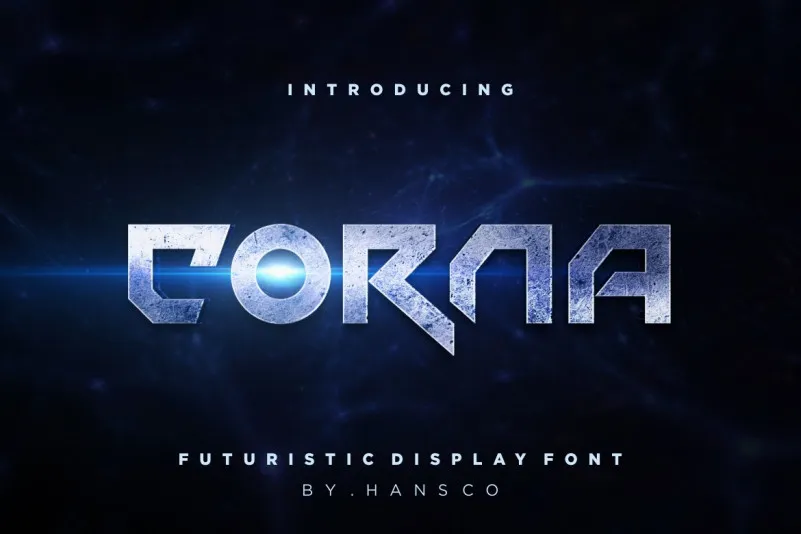
A Corna Font é uma nova escolha para quem busca uma fonte display moderna e forte. Desenvolvida pela HansCo, esta fonte oferece uma aparência limpa e retangular que destaca-se por sua agressividade e originalidade. Suas linhas são finas e definidas, criando um efeito visual impressionante. Ideal para aplicativos como posters, títulos de filmes, painéis publicitários ou cards de negócios, a Corna Font é uma opção ideal para empresas que desejam destacar-se com um design assertivo e inovador. E como sempre, mantemos o foco no nosso designer responsável por este projeto, 99designs, garantindo que continuamos a oferecer as melhores fontes de alta qualidade.